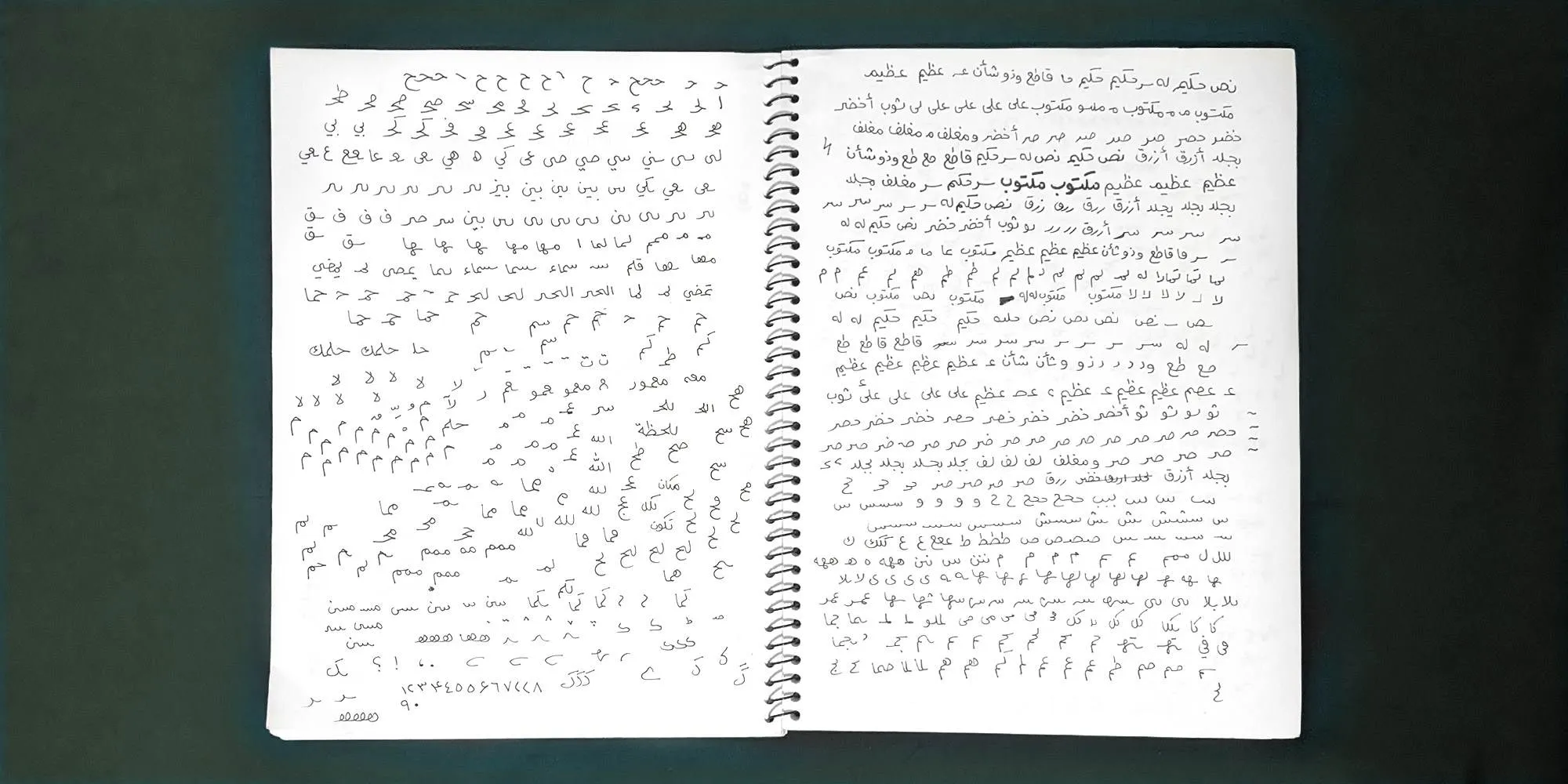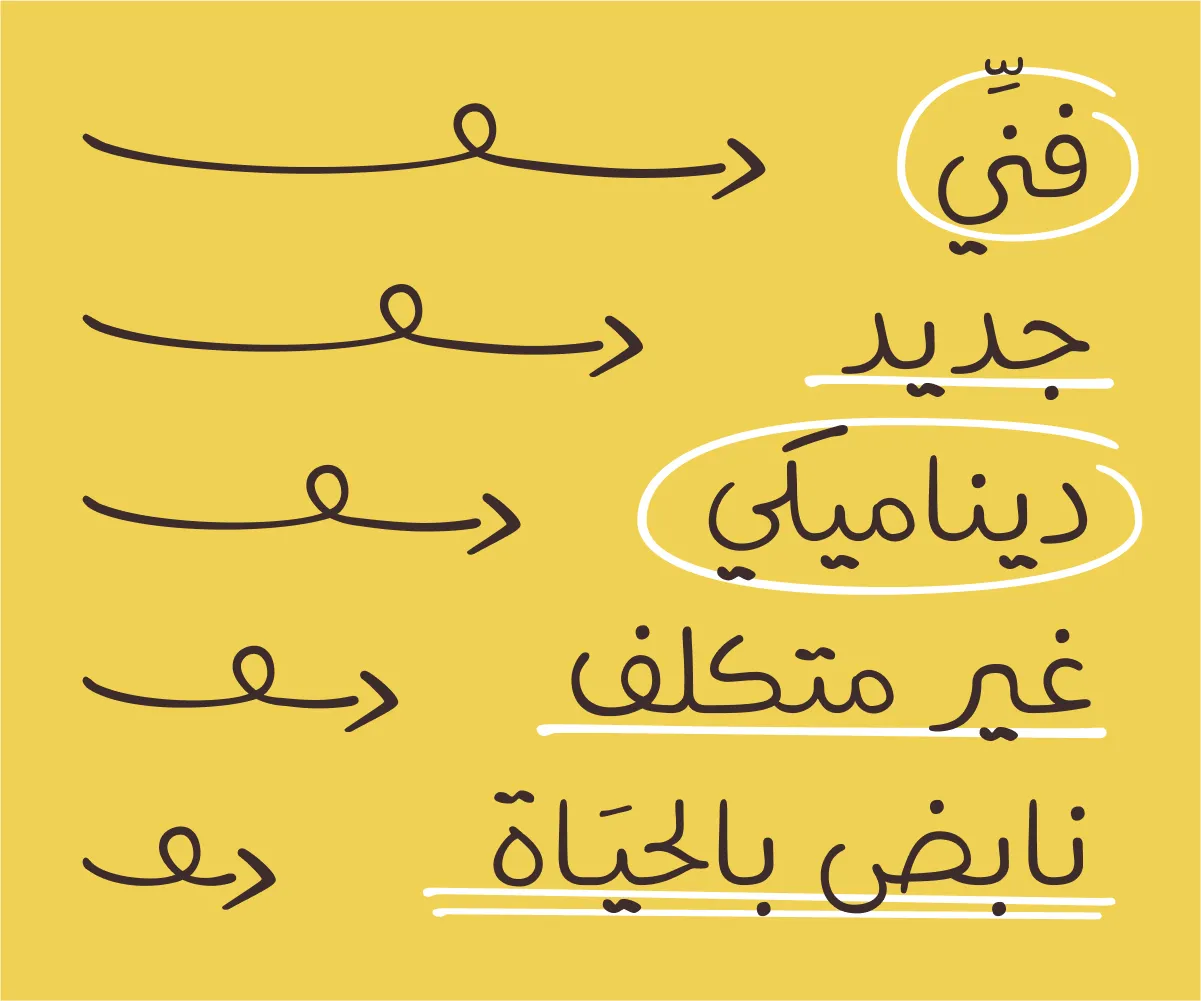
رقمنة الخطِّ العربيِّ تحدٍّ له بُعدٌ ثقافيٌّ وتقنيّ؛ إذ أنّ على روح التُّراث أن تُحفظ، وعلى قواعد العربيَّة أن تُطَوَّع، وعلى التَّفاصيل الأصيلة ألَّا تُختزَل. تصميم خطّ يحمل روح الكتابة اليدويَّة يرفع مستوى التَّحدي درجات عندما يضيف إلى المعادلة عامل «العفويَّة.» أعني بالعفويَّة أن تبدو الكلمات والجُمل كما لو أنَّها خُطَّت يدويًّا، وألَّا توحي لعين النَّاظر أنَّها مُبَرمجة رقميًّا.
نبعت فكرة خطّ تلحين من رغبتي بتصميم خطٍّ به شيءٌ من العفويَّة وأُلفة الكتابة اليدويَّة، مثل خطِّ زميلٍ في الفصل أو خربشاتٍ سريعة على هامش دفتر قديم. أردت أن أصنع خطًّا عفويًّا، سلسًا وغير متكلّف، بعيدًا عن الإتقان الميكانيكيِّ الذي يغلُب على الخطوط الرقميَّة المعاصرة.
يُعبِّر خط اليد عمَّن كتبه، ويُمثِّل بصمة تميزه عمَّن سواه. إلّا أن خطَّ الكتابة - بخلاف بصمة الأصبع - ليس دائم الشَّكل؛ فالأساس أنه يتحول بمرور الزمن، بل أنه يختلف باختلاف سرعة الكتابة وحتى باختلاف مزاج ومشاعر كاتبه في تلك اللحظة. قد يكون خط الشَّخص في الصباح مختلفًا عن خطه في المساء، وقد لا تُشبه كتاباته اليوم كتاباته بعد عام أو بضعة أعوام.
يراودني تساؤل دائم عندما أحاول رقمنة خط يدويّ: إذا كان الخط في جوهره خاصيَّة متغيّرة، كيف أستطيع تحديد هويَّة «خط يد» شخص معيَّن؟ هل هو تلخيص لأسلوبه الغالب في الكتابة، أم أنه توثيق للحظة زمنية مُحدَّدة؟ كيف لي أن أُجسِّد هويتي الخطّية في قالب رقمي ثابت بينما خطي في تحوُّل دائم؟
من البديهـيِّ أن هويَّتي الخطِّية — كجزء من شخصيّتي — تتغيُّر باستمرار؛ فطالما تتغيَّر شخصيَّتي بمرور الزَّمن وتراكم التَّجارب، ينعكس ذلك على تفاصيل حياتيَّة مثل طريقة تفكيري، وتعامُلي مع العالم الخارجيّ، وذوقي واختياراتي، وخطِّ يدي.
تخيّلت في هذا المشروع أنِّي ألتقط صورة فوتوغرافية أُجمِّد فيها مرحلة محددة من تطور خط يدي. عندما يلتقط المصوِّر صورة لشخص ما، فإنه يختار زاوية التصوير والإضاءة بعناية لتعكس أفضل ملامح له، أو لتنقل إحساسًا مقصودًا عبر عدسة الكاميرا. وعلى نحوٍ مشابه، راقبت أشكال الحروف التي أرسُمها في كتاباتي اليوميَّة في ظروف مختلفة لأحدِّد هويَّة هذا الخطِّ - عندما أُسرِع وعندما أتأنَّى، وعندما أركِّز على كلمة واحدة وعندما أكتب نصوصًا طويلة. وجدتُ توازنًا بين انسيابيَّة القلم وتناسق الحروف، حيث راقني أن الخطَّ حيٌّ وديناميكيٌّ به شيءٌ من العشوائيَّة المدروسة.
جرَّبتُ بضعة أقلام كي أختار أداةً تُبرِز تفاصيل خط يدي وتُبقي على انحنائاته الطبيعيَّة. بدأتُ من أقلام الحبر الجافَّة إلى السائلة، ومن السَّماكات الرقيقة إلى الثَّخينة. لاحظتُ تأثير نوع القلم على انحناءات أشكال الحروف ومرونتها، وتباين في السَّماكات لكل نصٍّ على الصَّفحة. النُّصوص المُسطَّرة بأقلام جافَّة بدت واضحةً ودقيقةً - وجدتها تفتقر إلى الانسيابيَّة التي أنشُدها في هذا الخطِّ، في حين أن الأقلام السائلة أتاحت المجال لمرونة أكبر، لكنها خلقت تفاوتات كبيرة في سماكة الخطِّ. استقرَّ اختياري في النِّهاية على قلم رسم وتحديد سائل بقطر 0.3 مم، حيث إنّه وازن بين الدِّقة والعفويَّة، وتجاوب شكل الحروف المخطوطة به مع ضغط القلم وإيقاع الكتابة الطبيعيَّة بشكل متناسق.
نبع اسم الخطِّ من هذه النُّقطة. أثناء اختياري المعيار الذي يحدِّد روح الخطِّ وأداة الرَّسم، وجدتني أميل إلى الاهتمام بالإيقاع البصريِّ للخطِّ، وفي تدفُّق الحروف بتناغم، ومن ثمَّ استوحيت اسم «تلحين» ليجسِّد هذا الإحساس.
على كرَّاسة رسمٍ رسمتُ الحروف وتنويعاتها بسُرعة كسرعة الكتابة الطبيعيَّة، وبعد تجارب وتعديلات تهدُف إلى مُحاكاة حركات يدي في الكتابة دون تكلُّف، وصلتُ إلى تشكيلة من حروفٍ توازنُ بين العشوائيَّة والتَّنظيم، حيث لم يطغَ شكلٌ على آخر. ولإضفاء بعضٍ من الفوضى اليدويَّة الجميلة، جرّبت تضمين شخبطاتٍ بسيطة مثل الأسهم والنجوم والرموز الصغيرة التي تتَّسق مع المظهر العام للخطِّ. صُمِّمت هذه الشخبطات لتُناسب كتابات غير رسميَّة أو مُنمَّقة، حيث أدرجها لاحقًا في الخطِّ لتظهر تلقائيًّا برموز معيَّنة في سياقات محدَّدة.
بعد أن نقلتُ الأشكال إلى برنامج صناعة الخطِّ «فونت كريتور،» عدَّلتُ تفاصيل الرَّسم لتناسب متطلبات الخطِّ الرقميِّ وتظهر الحروف كمجموعةٍ واحدةٍ بتباين سماكات وأحجام متقاربة. وبعد أن أنشأت جميع المحارف الحاليَّة في البرنامج، حانت مرحلة مراجعة الخطِّ ككُلّ والتَّأكد من انسجام الحروف كمجموعة. كان لا بدَّ من أن أضبط كل حرفٍ لئلّا يتصادم مع الحروف المجاورة له أفقيًّا ورأسيًّا. وبما أنَّ أشكال الحروف في الخطِّ متنوِّعة، فقد ظهرت تداخلاتٌ بين الحروف وعلامات التَّشكيل في حالات مُعيَّنة، ولذا خصَّصت قواعد إضافيَّة لتفادي هذه التَّداخلات وضمان سلاسة القراءة.
أدركت أن تراصُف الحروف جنبًا إلى جنب قد لا يكفي لتفادي الرَّتابة الرقميَّة. أردت أن تنسجم الحروف بطرق أقرب إلى الكتابة اليدويَّة، فأضفتُ تنويعات للأحرُف المركَّبة تجمع حرفين أو أكثر في شكل واحد، مثل «في،» و«ثم» بحيث تطرأ تغييرات طفيفة على شكل الحروف استنادًا إلى السياق الذي تظهر فيه.
أضفت أشكالًا بديلة إلى جانب الأحرف المركَّبة لتمنح المستخدم خيار تنويع أشكال الحروف في سياق النَّصِّ الذي يكتبه. كما يوحي به اسم هذه الخاصِّيَّة، فإنَّها تُبدِّل بعض الحروف بأشكال مختلفة بما يتناسب مع الحاجة أو الذَّوق الشَّخصيِّ. على سبيل المثال، يمكن للمستخدم أن يختار شكل حرف الكاف الوسطيَّة من شكلين يشبه أحدهما الكاف السَّيفيَّة، والآخر أقرب إلى الكاف الزّنادية في الخطوط التَّقليديَّة. من الأمثلة الأخرى شكل النُّقط في الحروف؛ أضفت خيارات تتيح للمستخدم اختيار التبديل بين النقطتين المتباعدتين، أو المتلاصقتين، أو المتراصّتين رأسيًّا فوق بعضهما. وبالنسبة للثلاث نقاط، يمكن أن تُبدَّل بين المنفصلة أو المتصلة لكسر الرَّتابة في الخط.
مشروع خط تلحين محاولة لإحياء تجربة الكتابة اليدويَّة بما تحمله من فوضى جميلة؛ ولا تكتمل هذه التجربة بدون خرابيش عفويَّة تتخلَّل النُّصوص وتحاوِطها. اخترت من الرُّسومات الأوَّليَّة بضعة رُموز كوجه مبتسم وقلب ونجوم وخطوط تزيينيَّة تلائم الخطَّ الرقميّ. حرصت على أن تصبح هذه الشخبطات جزءًا طبيعيًّا من تجربة الكتابة، فبرمجتُها لتظهر تلقائيًّا في سياقات معيَّنة. على سبيل المثال، عندما يكتب المستخدم كلمة تليها -- (شرطتان متتابعتان)، يظهر خطٌّ تحت تلك الكلمة تلقائيًّا، وعندما يكتب كلمة *زهرة*، تُرسَم زهرةٌ بأسلوب الخطِّ نفسه بجانب النَّصِّ المكتوب. الفكرة كانت أن تمتزج هذه الرُّموز بسلاسة مع النص فتُضفي لمسة شخصيَّة، دون أن يحتاج المستخدم إلى إدراج رموز يدويًّا.
في جُعبتي خططٌ لتطوير تلحين بمزيدٍ من الرُّموز والزَّخارف والكشائِد، وتنويع أشكال الحروف، بل وأطمح إلى تطوير الخطِّ اللَّاتيني المُتوافق. هدفي أن يكون تلحين خطًّا مُتكاملًا صالحًا لمُختلف الاستخدامات، وأن أقتربَ قدر ما أستطيع من الصُّورة الَّتي أتخيَّلُها للخطِّ «العفويّ.» تصميم الخطوط الرقميَّة عمليَّة تحسين وتطوير دائمة مع كلِّ استخدام جديد للخط. وهذا ما يُحوّل الخطوط إلى تجربة حية تتكيف مع كل سياق تُستخدم فيه.